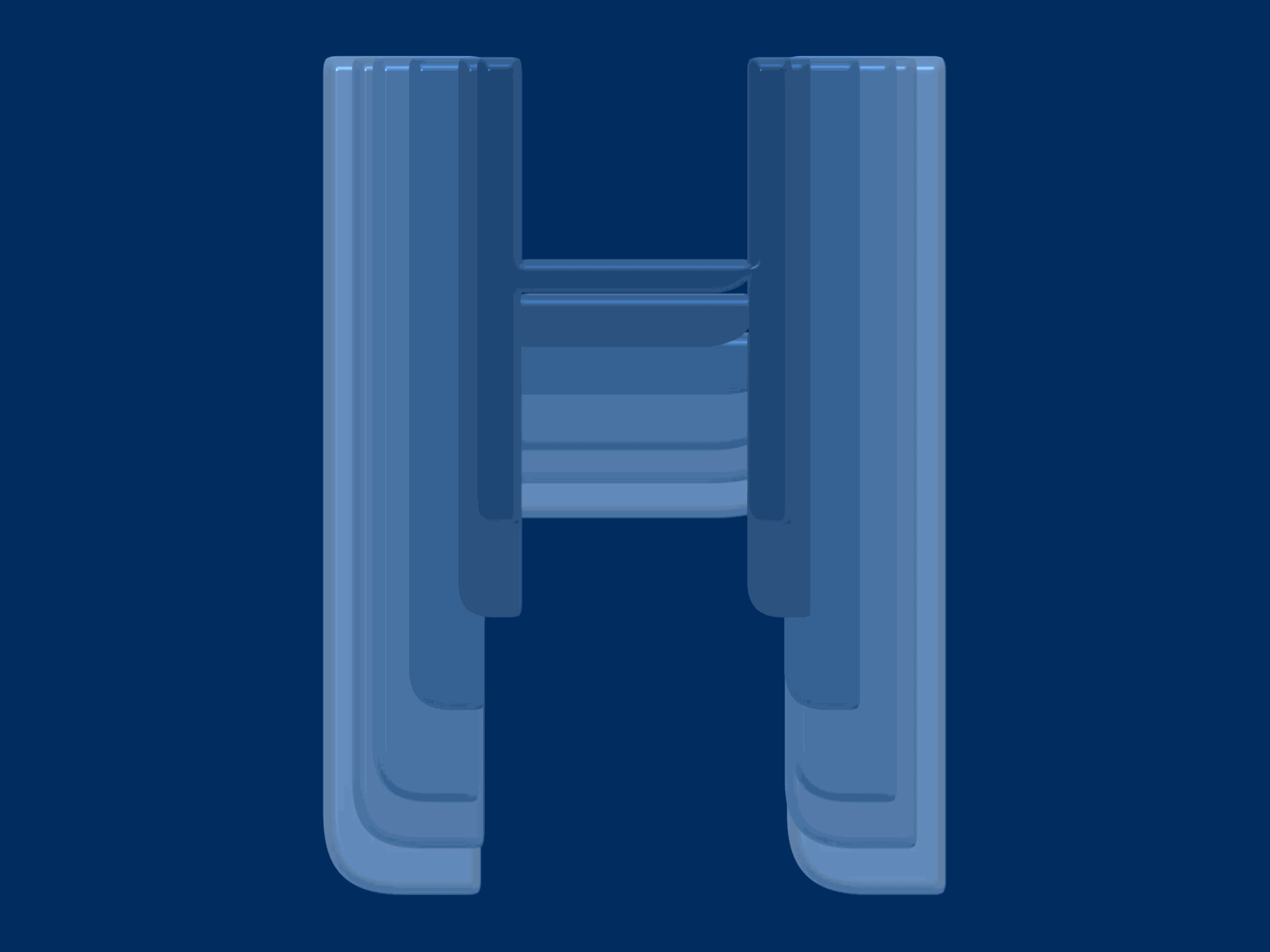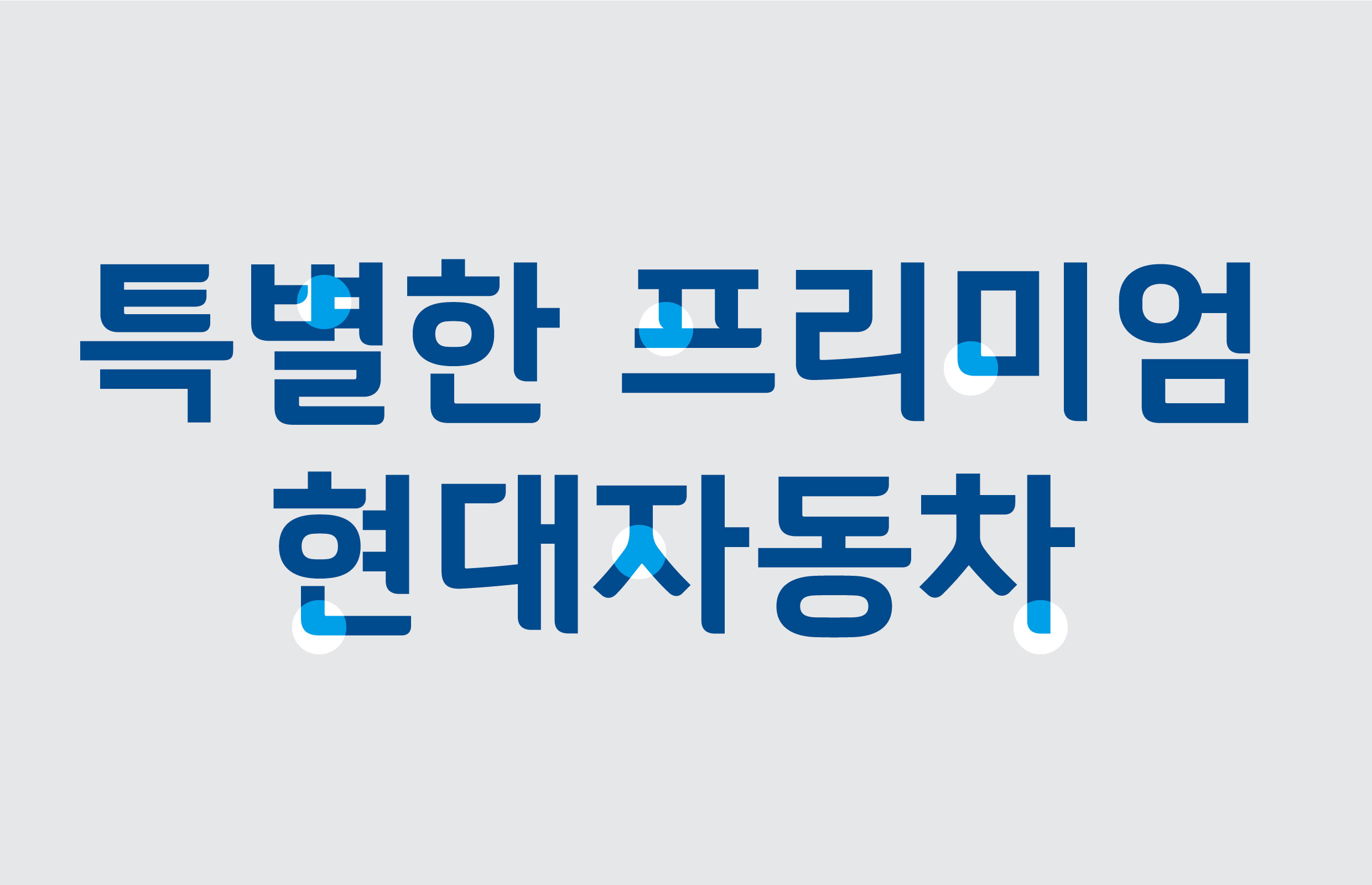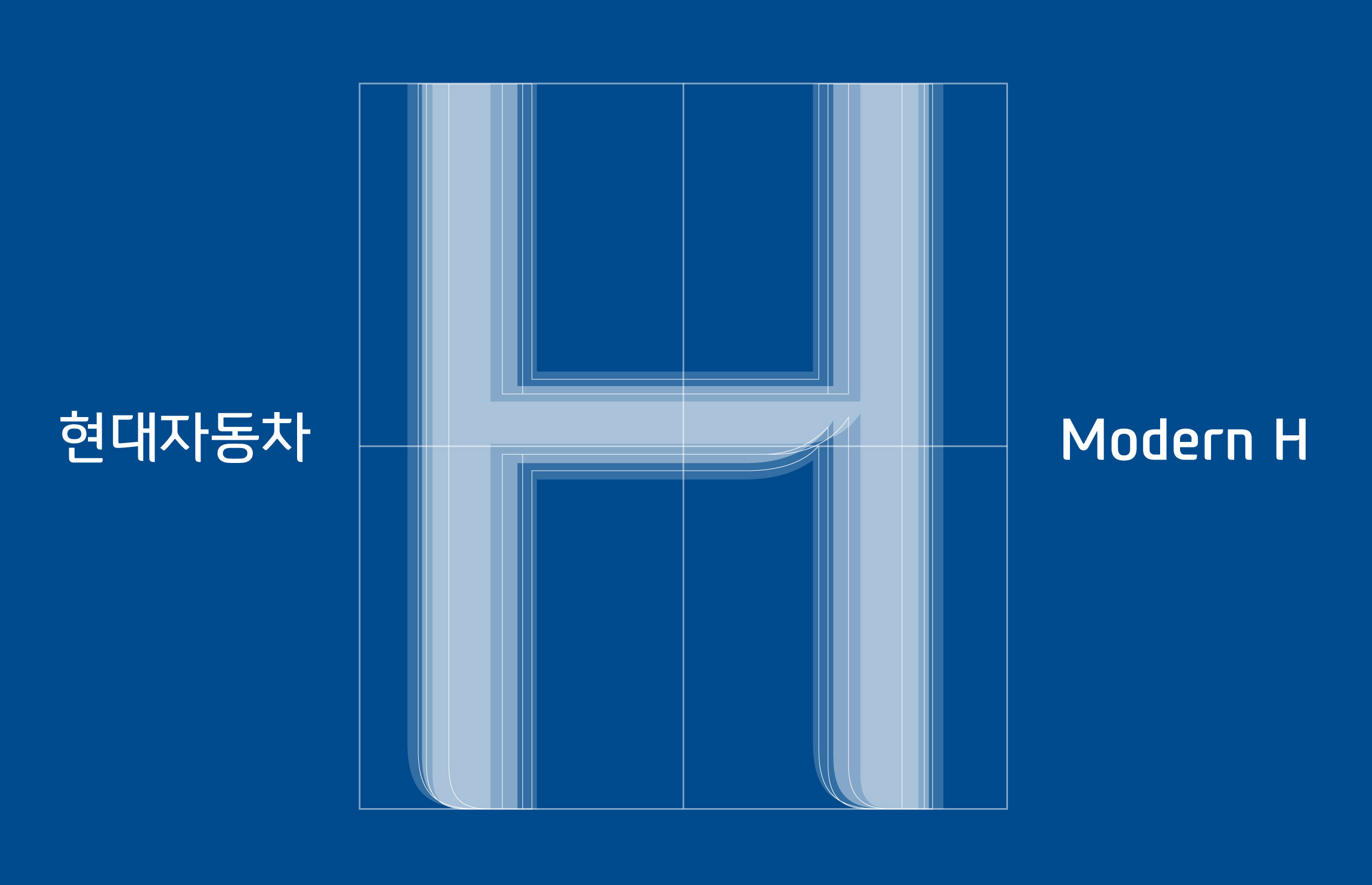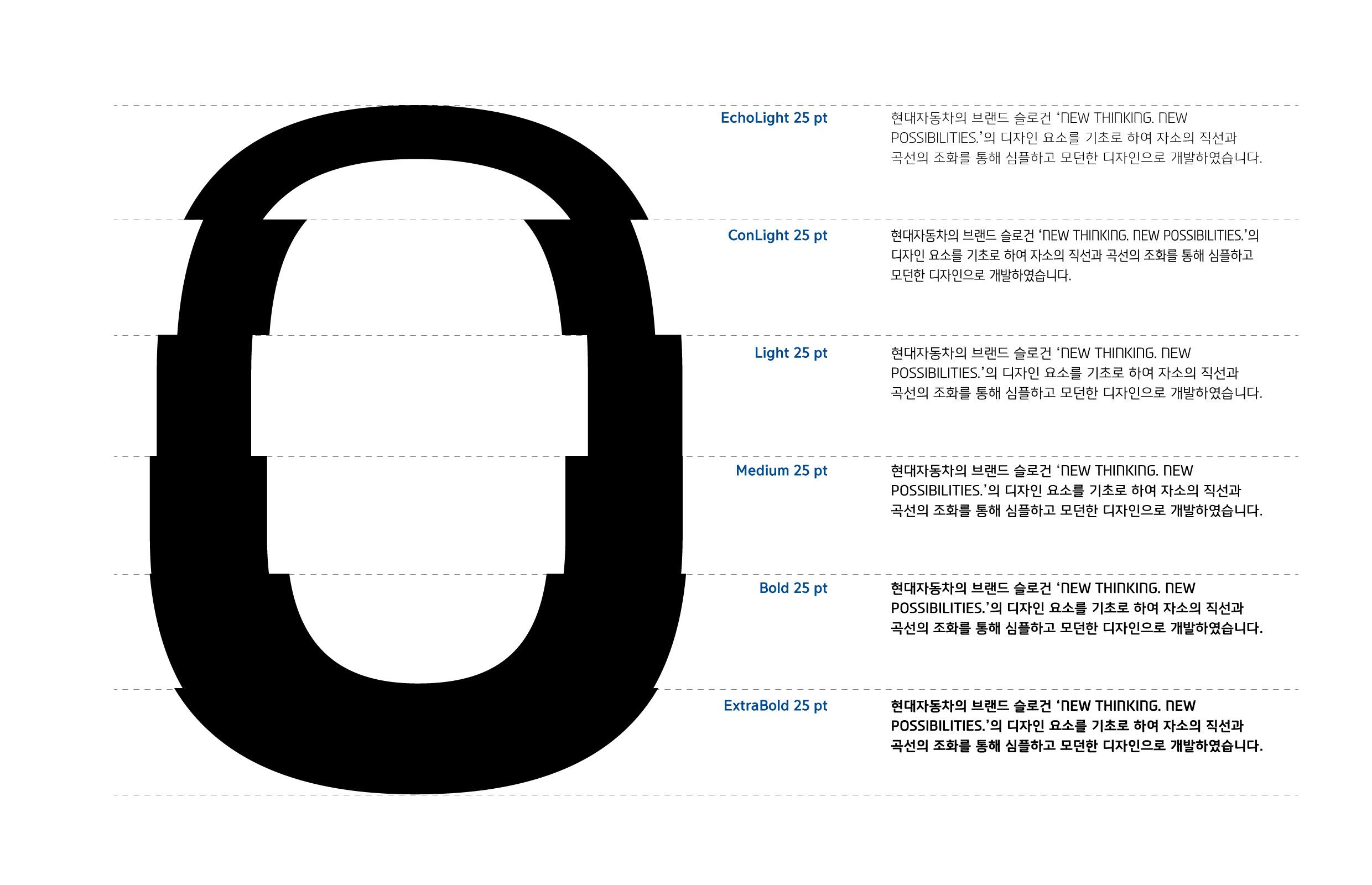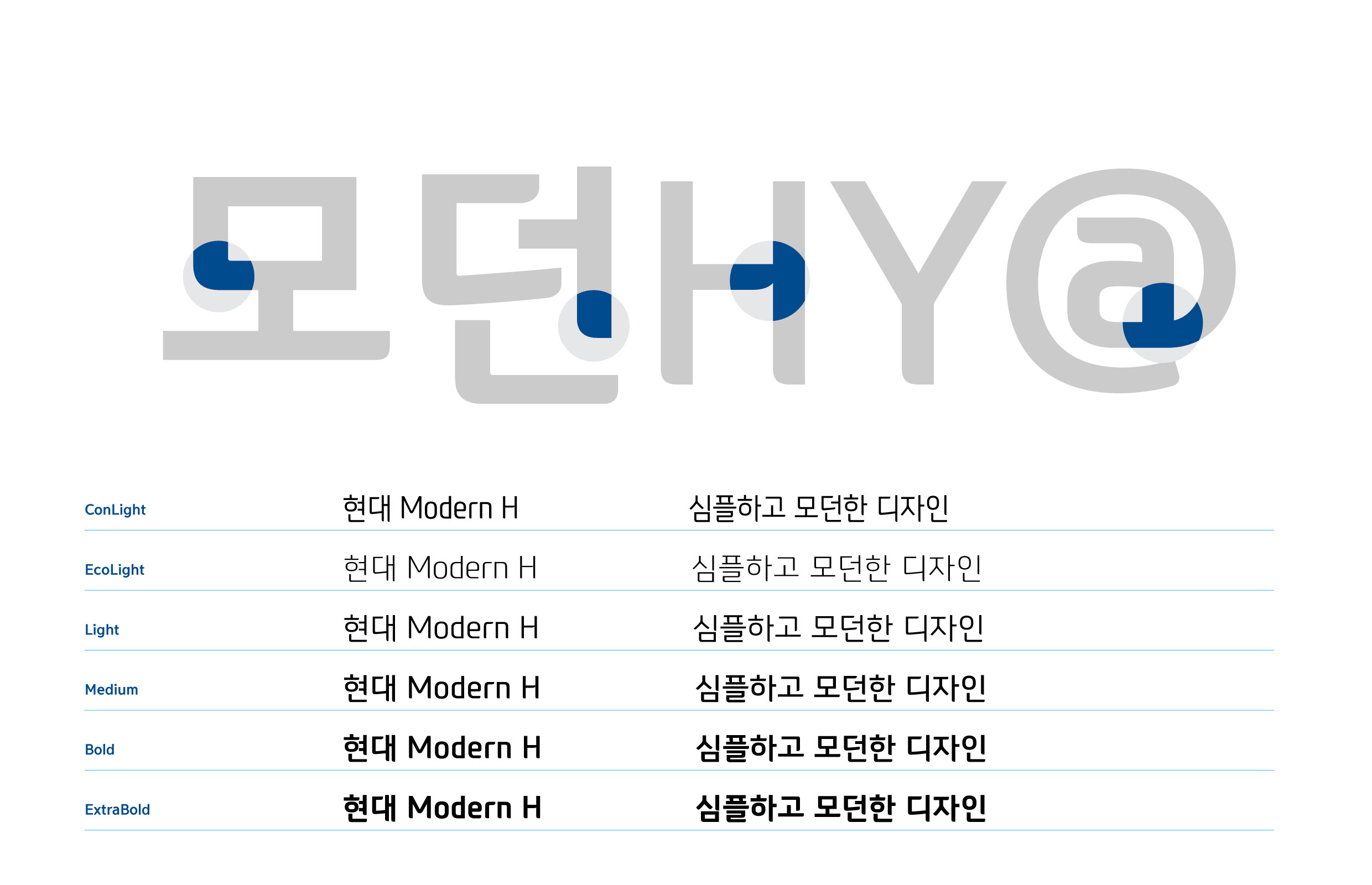
현대자동차 [Modern H]
현대자동차 전용서체는 변함없는 열정과 창조의 정신으로 다이나믹한 실행력을 갖춘 현대자동차의 이미지를 담았으며, “세련되고 당당한” 현대자동차의 아이덴티티를 담아 4가지 굵기로 개발했다. 라틴 알파벳 서체는 기존 슬로건의 ‘N’을 모티브로 세련되고 고급스러운 이미지를 강조하였으며, 한글 서체에도 라틴 알파벳의 독특한 특징을 접목시켜 일관성을 유지했다.